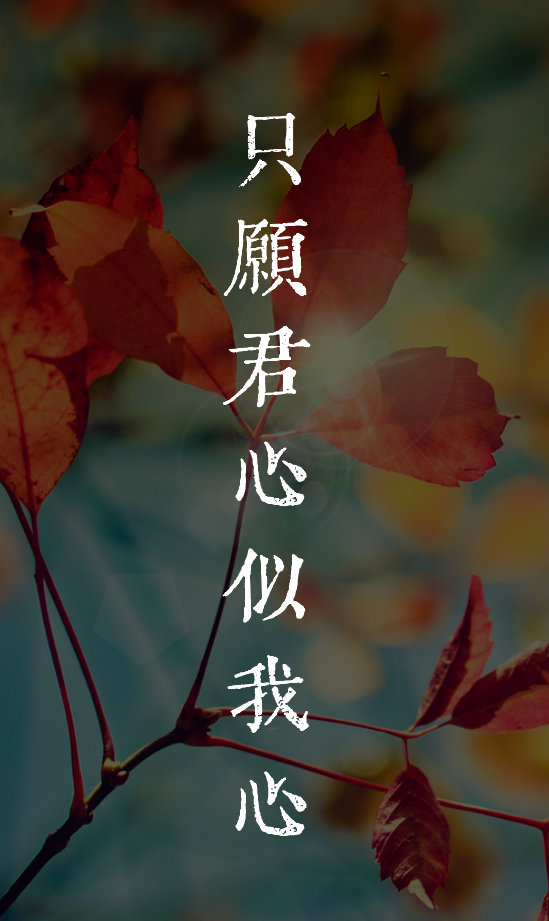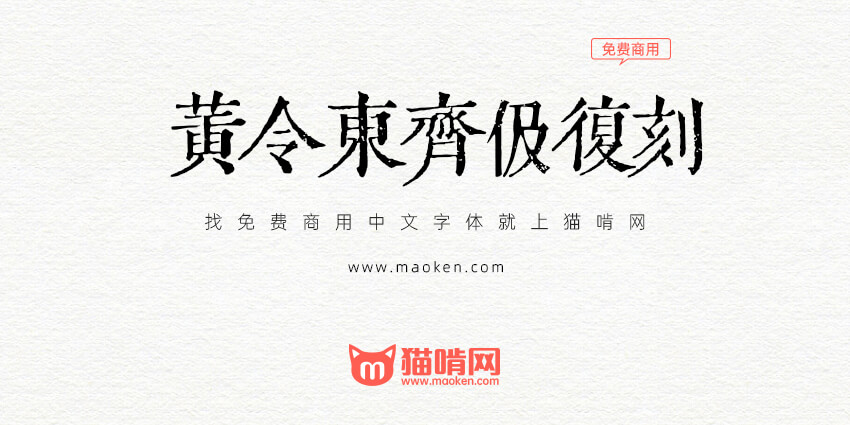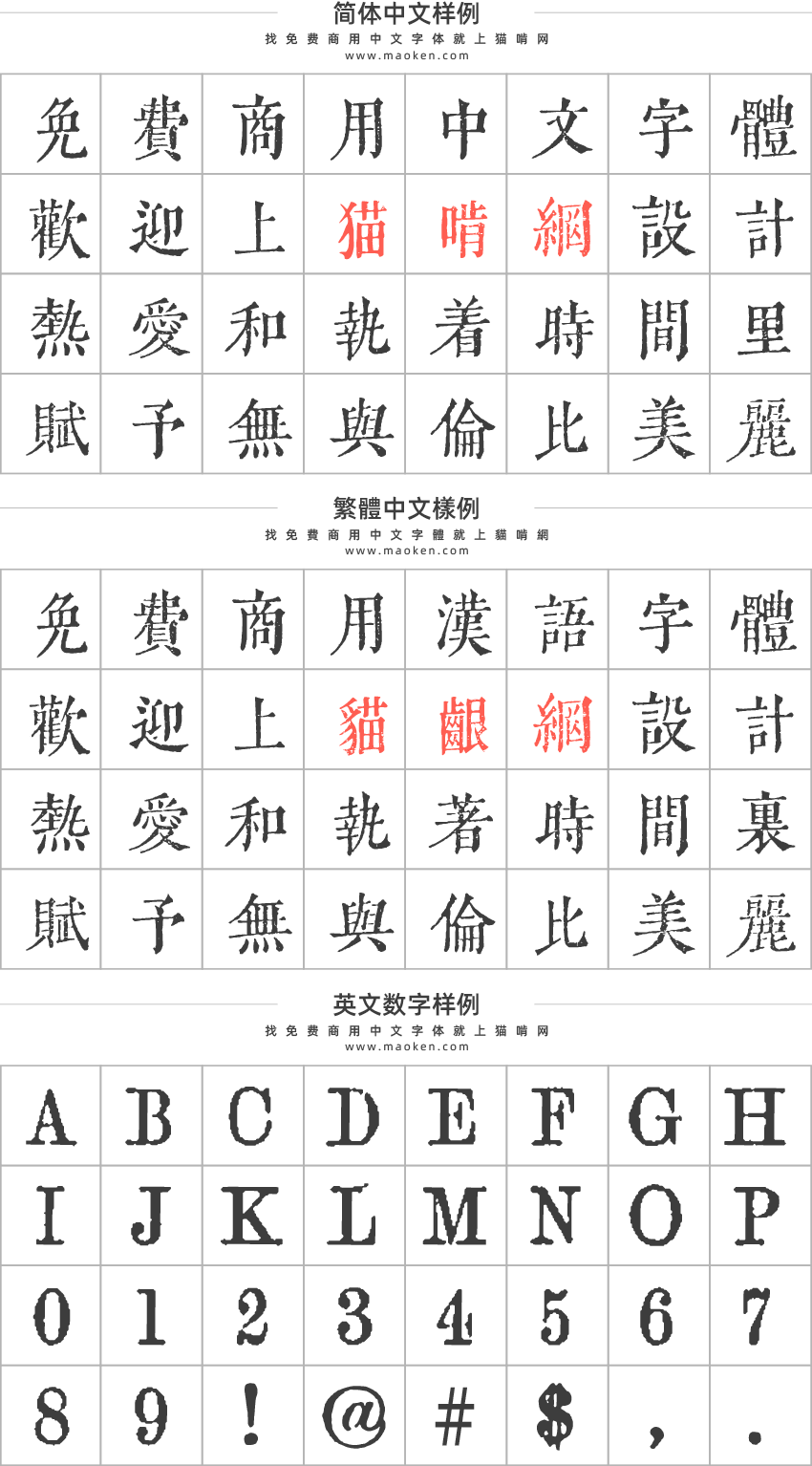
黄令东齐伋复刻:精品华夏文字传承复刻字体免费商用
字体作者:黄令东 (中国大陆) 字体字重:1个
之前猫啃网推荐过《黄令东齐伋体》给大家,这是一款充满了古典气质的,可媲美康熙字典体的字体,深受大家喜爱。而齐伋体是分两个版本的,一个是Combo版,一个是Fallback版。Fallback版本即之前介绍的黄令东齐伋体。为了方便区分,猫啃网把Combo版本叫做黄令东齐伋复刻,这样比较容易理解。
黄令东齐伋复刻采用半自动计算机视觉和OCR对《李長吉歌詩》《淮南鴻烈解》进行扫描,通过程序处理后再手动选择适合的字型,最后导出成字体文件。
在扫描完字体之后,再从中挑选合适合的字形进行微调处理,最后再把结果输出为字体文件。
黄令东齐伋复刻是对古籍进行处理而得到的字体,所以只有繁体字形。在使用字体的过程中,如果输入简体字会直接映射成繁体字形。比如说你输入“汉”字,出来的结果会是“漢”字。这个结果不难理解,古人不会写简体字。
这个的英文是从哪来的怎么打不出来
“大”字在竖排排版会横过来是咋回事
要是有与之相配的英文、数字就完美了。ε=(´ο`*)))唉
• EB Garamond、Linux Libertine这些应该可以
这个更新的版本,英文又没有了!还有字体名称又变成qiji了,不是汉语的名称
• 因为原来有英文的,是zfont站长加上去并改名的~
• 1.字体名称是字母qiji
2.没有数字和英文字母
上述2项在原版中一直是这样的,如果您发现了问题可以直接在github向原作者提交bug。
之前确实有Zfont的站长自己调整二改了一版【黄令东齐伋复刻修改版】,
增加了风格相似的Oradano-Mincho数字英文,并调整字体名称显示为中文。
但这是二改的字体,和原作者的原版调整没关系。
QIJIC 齐伋复刻体 v0.0.2 字形 bug: “珍 ”字下面,有多余的横线未清除干净
我这里使用的情况看,这个字体里的“大”字严重偏上偏左。
• 这个是用程序自动处理的字体,有些字可能会存在一点问题~~
古籍裡沒有這個字就用思源宋體韓文版的字代替
这个应该属于二改字体了吧,去zfont看了下,增加的是【Oradano-Mincho 明朝日文字体】的数字和英文